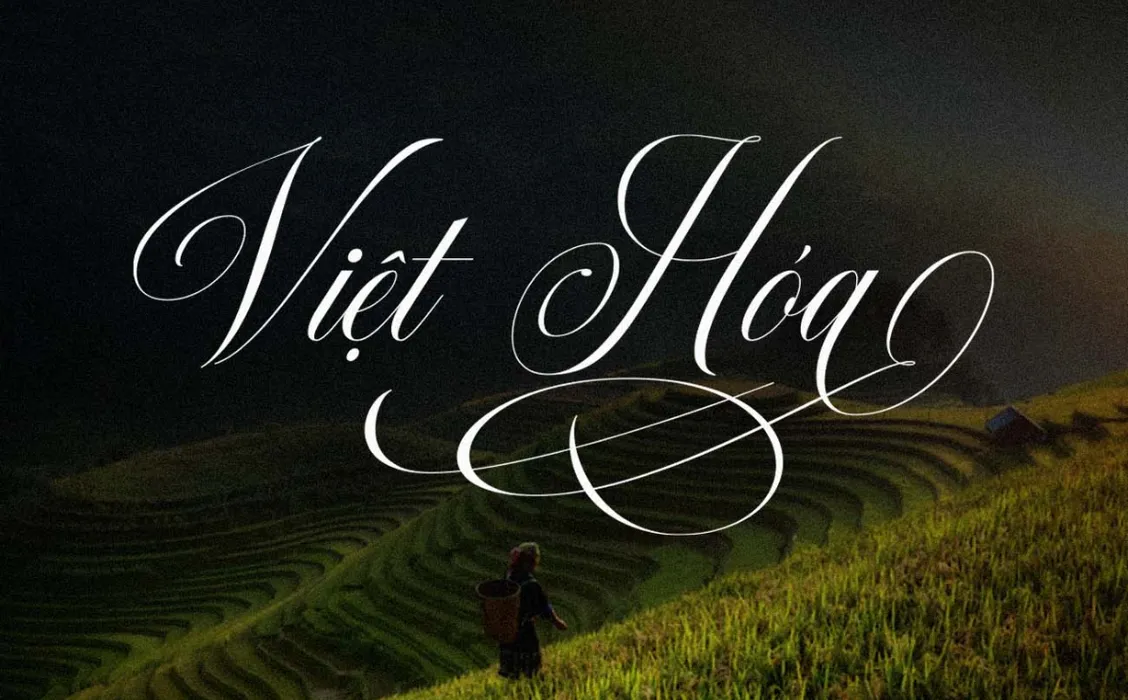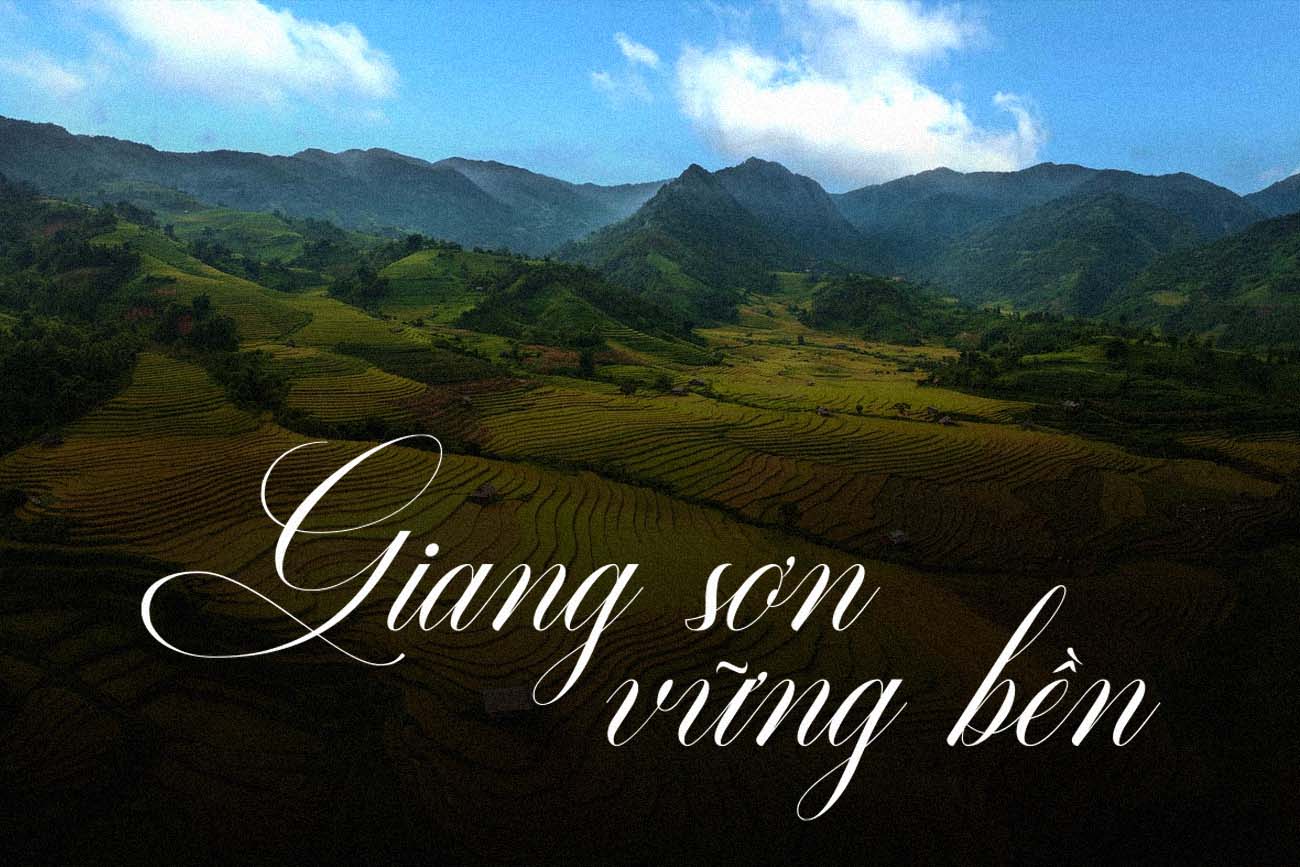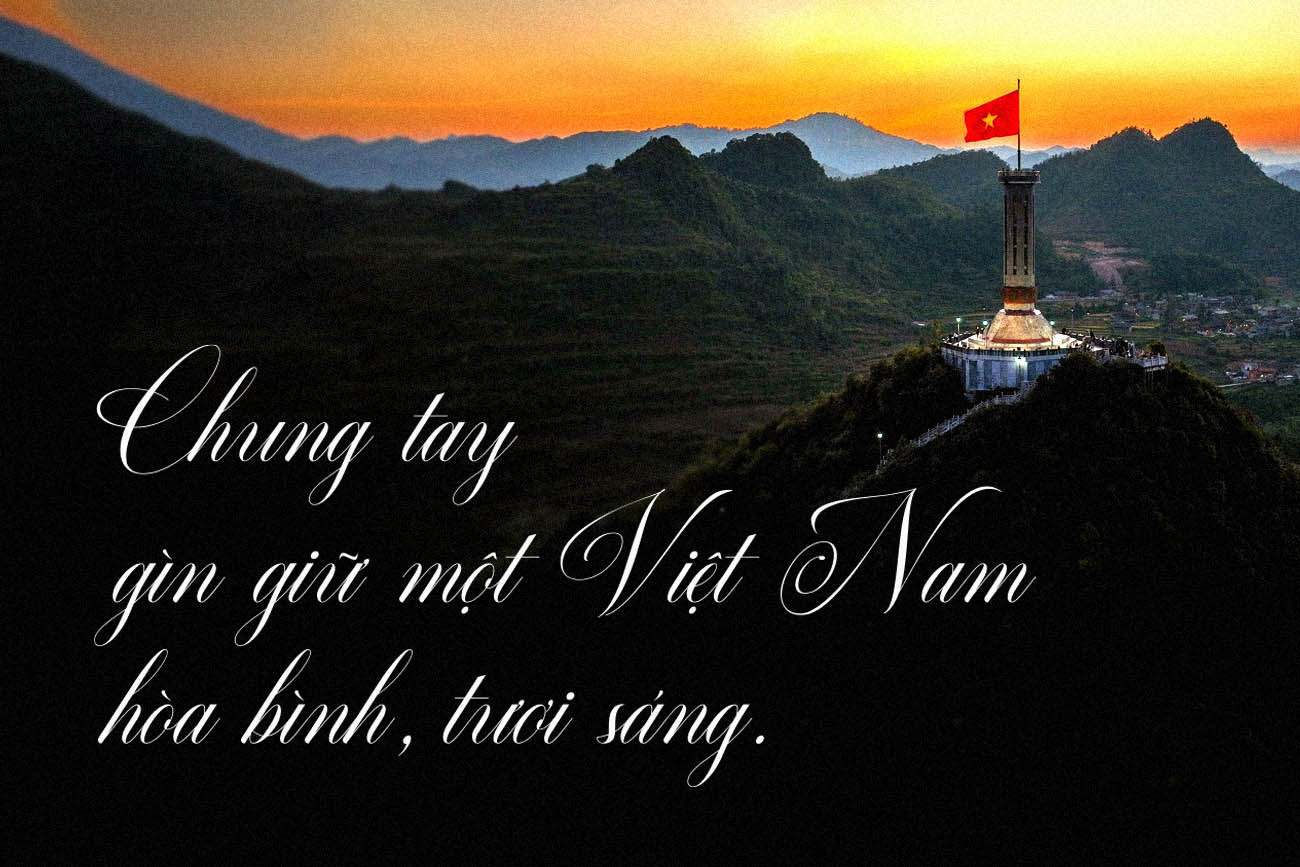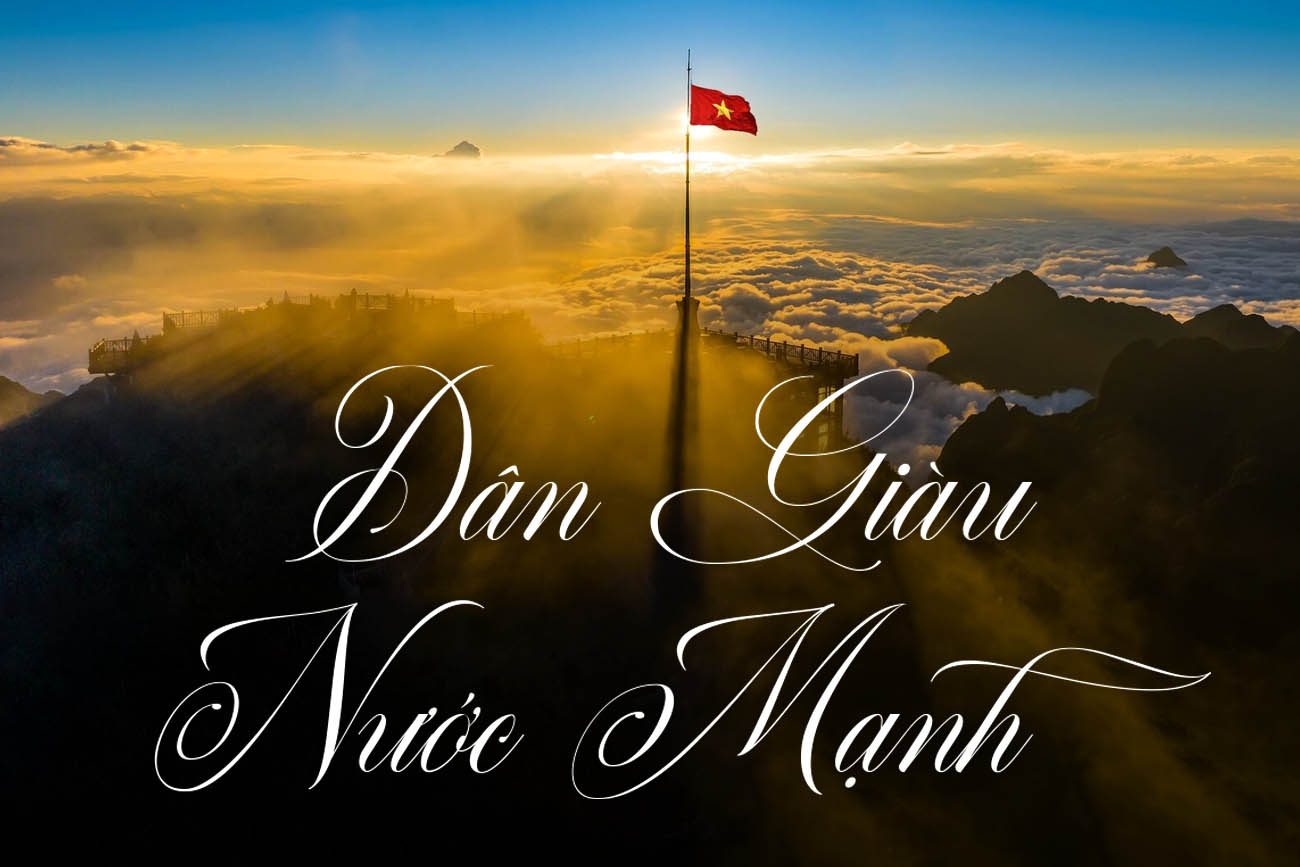
Mang trong mình hơi thở lãng mạn và nghệ thuật, TH Quadrien (phiên bản Việt hóa từ font gốc của nhà thiết kế Ramzehhh) là mảnh ghép hoàn hảo để hiện thực hóa những ý tưởng thiết kế tiệc cưới sang trọng và bay bổng. Đây là dòng Script cao cấp, mở ra không gian thị giác tràn đầy cảm xúc cho ngày trọng đại.
Vũ điệu của những đường nét: Điểm thu hút nhất của bộ font chính là sự chuyển đổi mượt mà, uyển chuyển giữa các nét thanh và nét đậm. Từng ký tự được thiết kế với độ nghiêng hoàn hảo, tạo ra nhịp điệu thị giác vô cùng bắt mắt.
Phá vỡ sự cứng nhắc: Cấu trúc uốn lượn mềm mại với những đường kéo dài ở phần đuôi chữ được tính toán tỉ mỉ, giúp các tác phẩm typography trở nên có hồn, nghệ thuật và thu hút ánh nhìn ngay từ giây phút đầu tiên.
Lựa chọn hoàn hảo cho Wedding & Branding: Phù hợp tuyệt đối để thiết kế thiệp cưới, bảng chào mừng, logo thương hiệu cao cấp hay các ấn phẩm cần tôn vinh sự tinh tế, sang trọng.
Với bản Việt hóa chỉn chu, TH Quadrien Script giúp dòng chảy tiếng Việt hiện lên mượt mà như một bức tranh thư pháp hiện đại, là công cụ không thể thiếu trong kho tài nguyên của mỗi Designer.